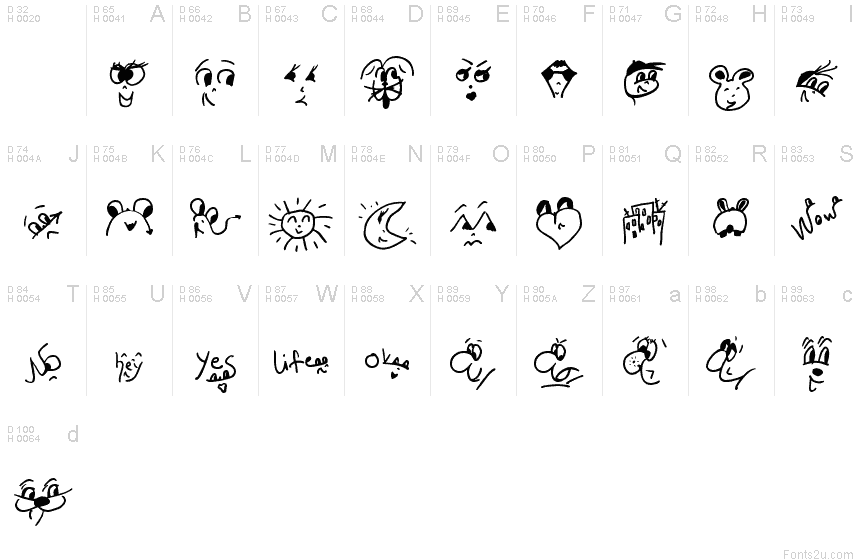
Life Is Life autorstwa Fenia to darmowy, odręcznie rysowany font piktogramowy przedstawiający proste motywy zwierzęce. Luźna kreska układa się w sylwetkę przypominającą królika z dużymi uszami i wydłużonym ogonem, co nadaje znakowi bezpośredniość szybkiego szkicu tuszem.
Młodzi odbiorcy są najlepiej dopasowani do tego swobodnego stylu rysunku. Może on ożywić wydawnictwa dla dzieci, artykuły dziecięce, kartki okolicznościowe oraz nieformalne opakowania. W tych zastosowaniach stworzenie może pełnić funkcję zarówno znaku, jak i ilustracji.